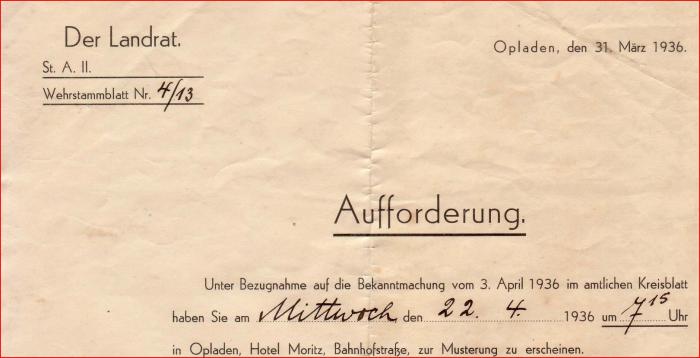
verwendete Schrift von 1936 gesucht
ich wüsste gerne wie die in diesem Ausschnitt von 1936 verwendete Schrift heißt. Futura ist nicht richtig. Das abgerundete "b" stimmt nicht, vielleicht eine Hausschrift? In einem Suchprogramm versucht, ohne Erfolg.
Gelöst von Erwin Krump
Another type that has a long history of doubles and renaming was first known as Kristall Grotesk,
an in-house design by the Leipzig-based Wagner & Schmidt type foundry. The many versions
can be distinguished by alternate character sets (e.g. some fonts come with a single story ‘a’,
while others feature the double-story alternative).
According to Philipp Bertheau’s Atlas zur Geschichte der Schrift, a comprehensive encyclopedia
of typefaces, Kristall Grotesk was revived and released under these names in the following years:
as Polar Grotesk (or simply Polar) in 1930 by J. John Söhne in Hamburg; as Rund Grotesk
with C. E. Weber, Stuttgart, in 1931 and once more as Kristall Grotesk with the Norddeutsche
Schriftgießerei in Berlin. It was apparently released abroad as Saxo with the Berling type foundry
in Sweden and as Predilecta with José Iranzo in Spain. In reference to its original name
(spelled slightly different) it was distributed as Krystal-Grotesk in Denmark.
danke an alle, die so schnell antworteten. Polar Grotesk, das war wahrscheinlich die Version, die die Druckerei 1936 nutzte. Die Erbar kommt der Type auch schon sehr nahe.